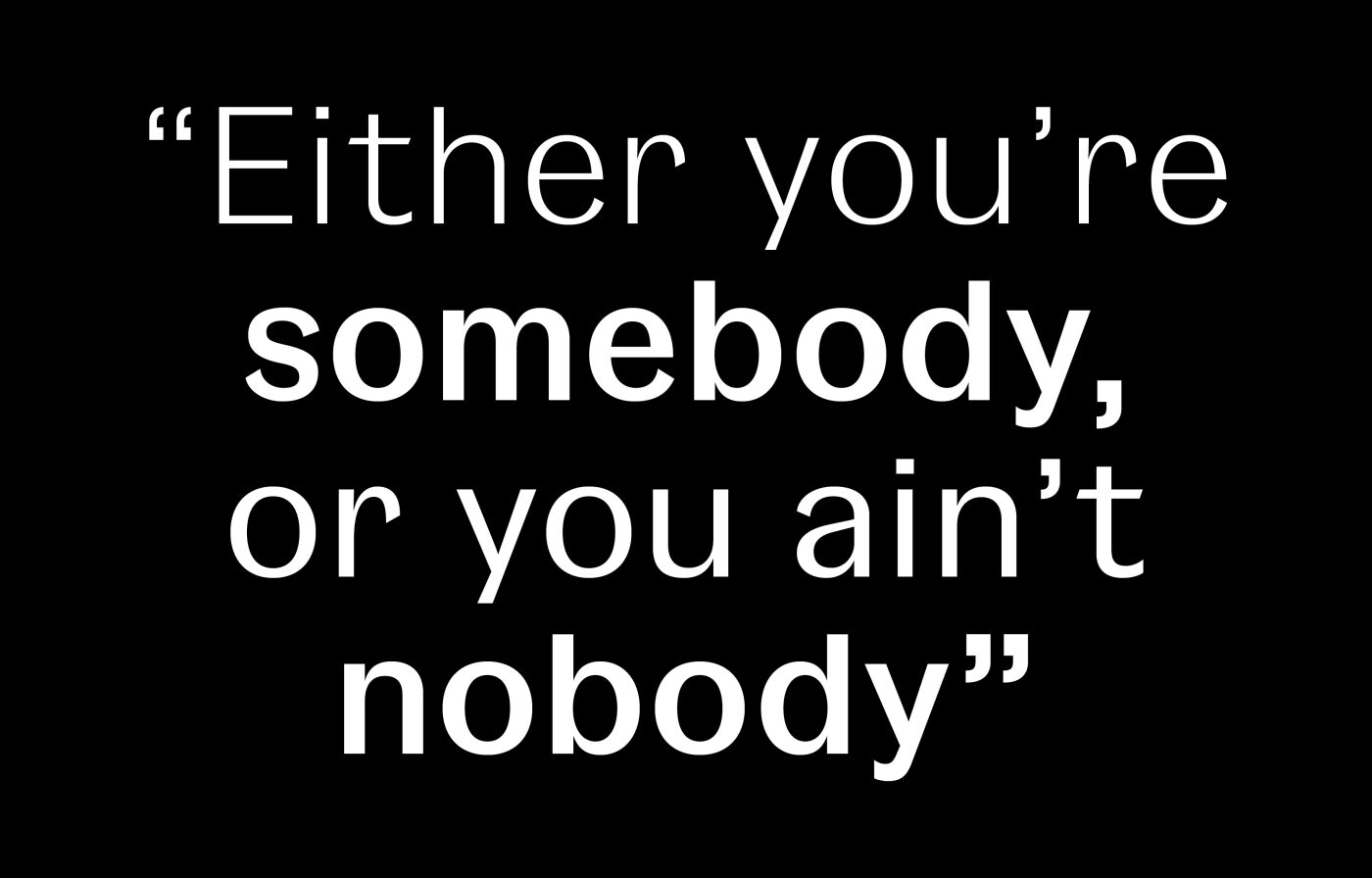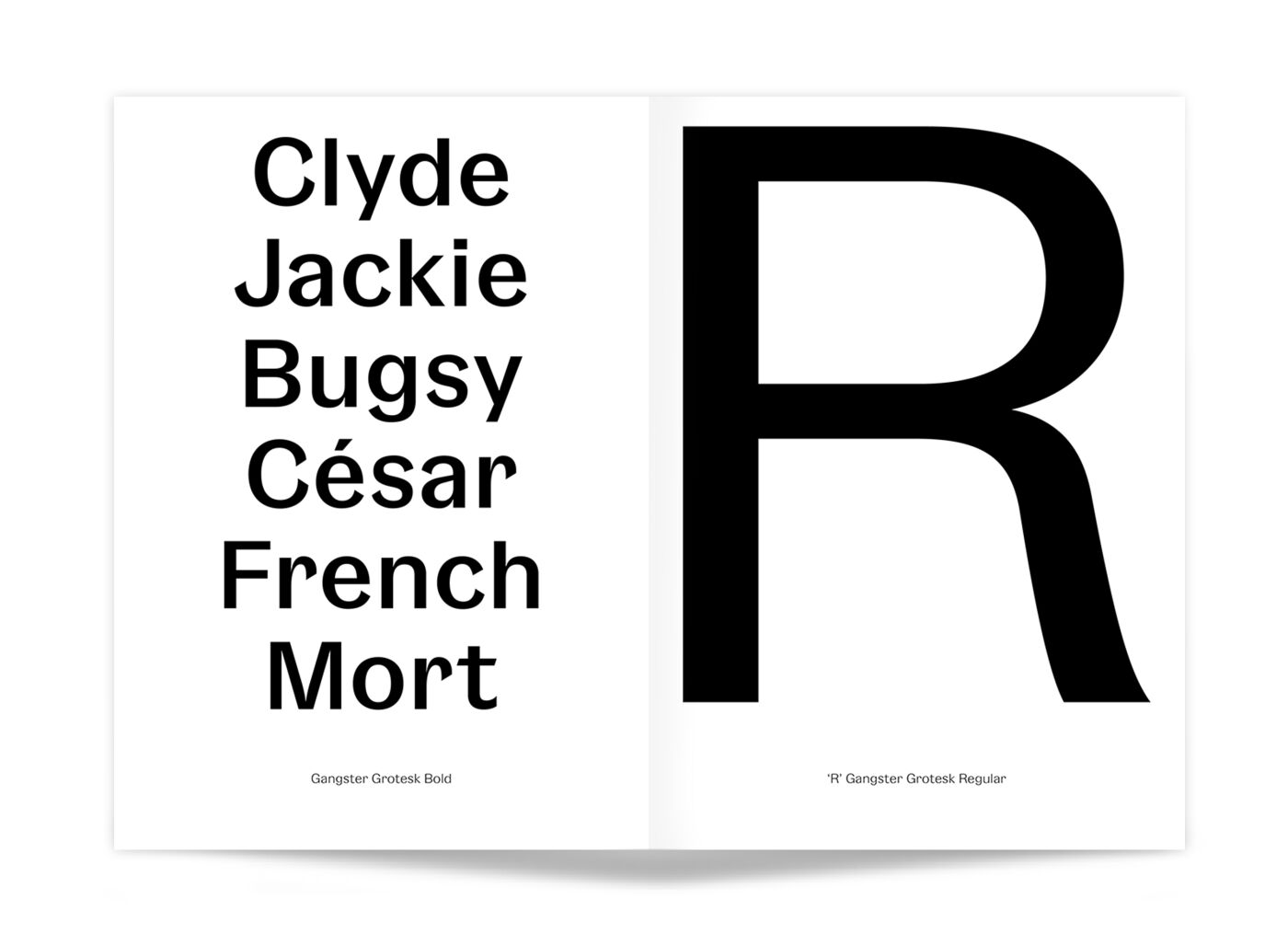
Gansgter Grotesk
Inspirée des premières "grotesques" des années 1920, Gangster Grotesk est une police de caractères contemporaine qui associe un contraste entre pleins et déliés et des terminaisons fermées. Ces caractéristiques sont simples, reconnaissables et efficaces, prêtant à cette police de caractères un charme prenant toute son ampleur en grande taille et presque invisibles en petites tailles.